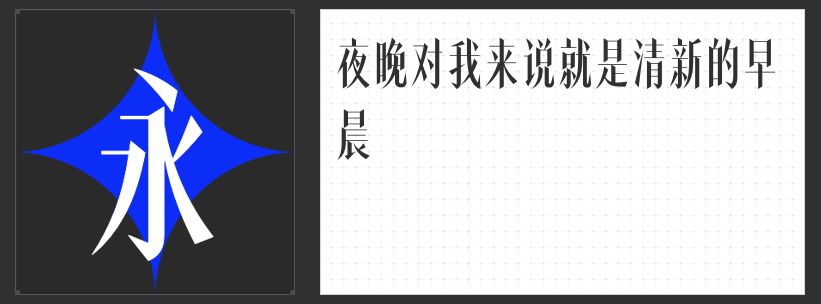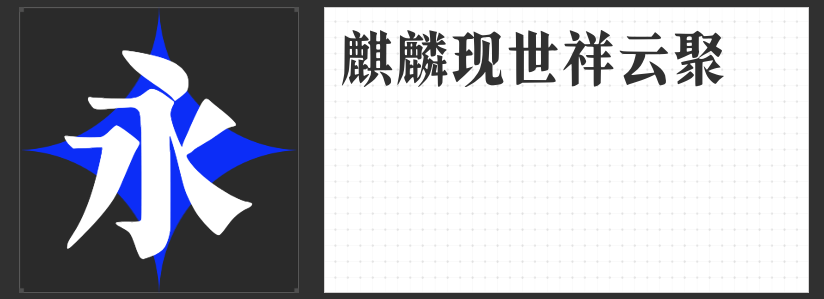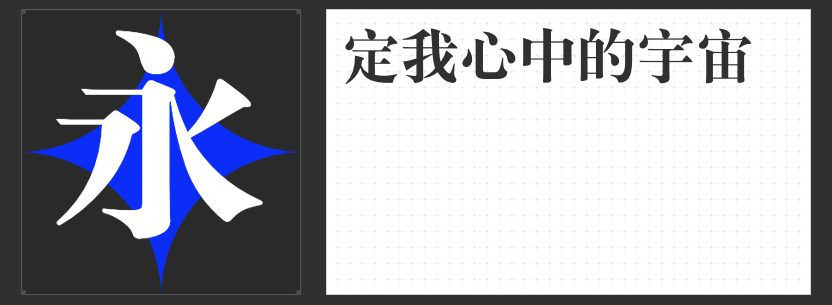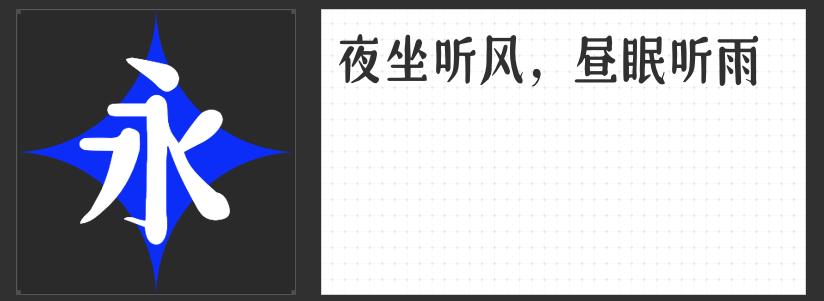
四款宋体佳作:以笔墨匠心唤醒时光深处的怀旧诗韵
在当代设计的语境中,宋体字以其横细竖粗的骨骼、收放自如的笔画与温润典雅的气质,始终占据着文化表达的核心位置。当传统宋体的规整与现代设计的怀旧情怀相遇,四款独具匠心的宋体字体以不同姿态诠释着东方美学的传承与创新,为设计注入跨越时空的视觉温度。
一、励字大标宋简繁
这款字体以老宋体的筋骨为基底,融入黑体的现代感,形成横轻竖重的鲜明对比。笔画末端三角状的装饰细节,既保留了雕版印刷的刀刻痕迹,又通过尖端设计赋予灵动气息。其字形端正而不失清秀,在庄重与轻盈间找到微妙平衡,仿佛将旧书页的墨香与金属活字的冷峻熔铸于一体,适合需要传递历史厚重感的设计场景。
二、高手庆科自由宋 大宋
以手写感为灵魂的高手庆科自由宋 大宋,突破传统宋体的几何框架,通过圆润的笔画与适度的瘦长结构,营造出流动的韵律感。横画末端的圆形装饰角与细长上挑的钩画,如同书法家运笔时的自然回锋,让每个字符都蕴含着呼吸般的生命力。西文字符的圆润处理更与中文形成和谐共鸣,在东西方美学碰撞中绽放出独特的趣味性。
三、高手兵克高雅宋
这款字体以修长字形勾勒出宋体的优雅轮廓,转折处的尖角处理暗合宋代瘦金体的飘逸神韵,而竖画收笔的向左切口则如琴弦轻颤,为刚劲的笔画注入一丝婉约。整体设计在克制中见精妙,仿佛用现代设计语言重新诠释了文人墨客的笔墨情怀,适合需要表达高雅格调的文化类设计。
四、机甲宋麒麟号
当宋体的柔美笔触邂逅机甲的硬核美学,这款字体以冲突感创造视觉记忆点。修长的字形延续宋体纵向舒展的特质,而笔画中融入的机械线条与几何切割,则让每个字符都仿佛由金属锻造而成。这种刚柔并济的设计思维,既保留了传统书法的文化基因,又为科技主题的设计开辟了新的美学维度。
这四款宋体字体,或以经典为骨,或以创新为魂,在横竖撇捺间编织出怀旧与现代交织的视觉叙事。它们不仅是文字的载体,更是连接过去与未来的设计媒介,让每一次笔画的舒展都成为穿越时空的文化对话。